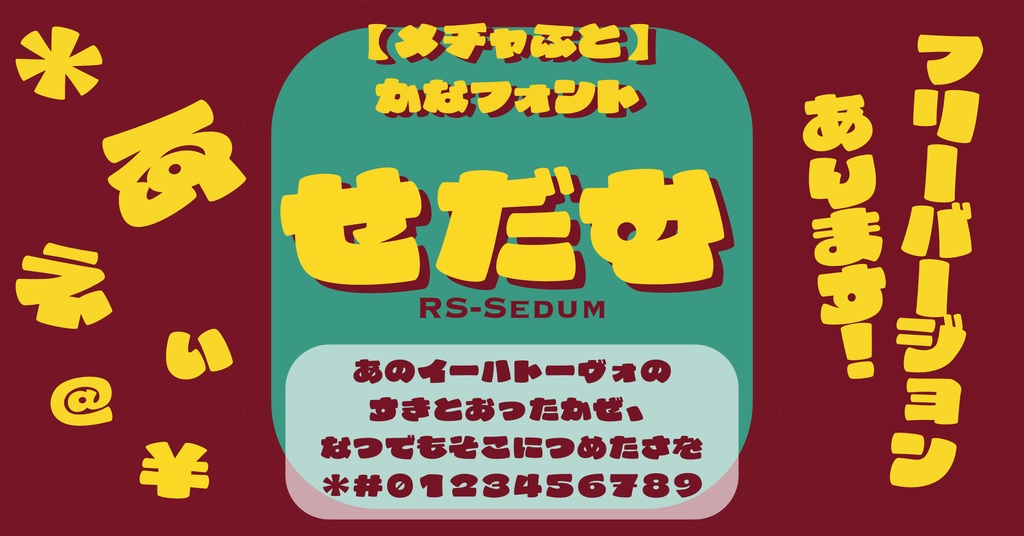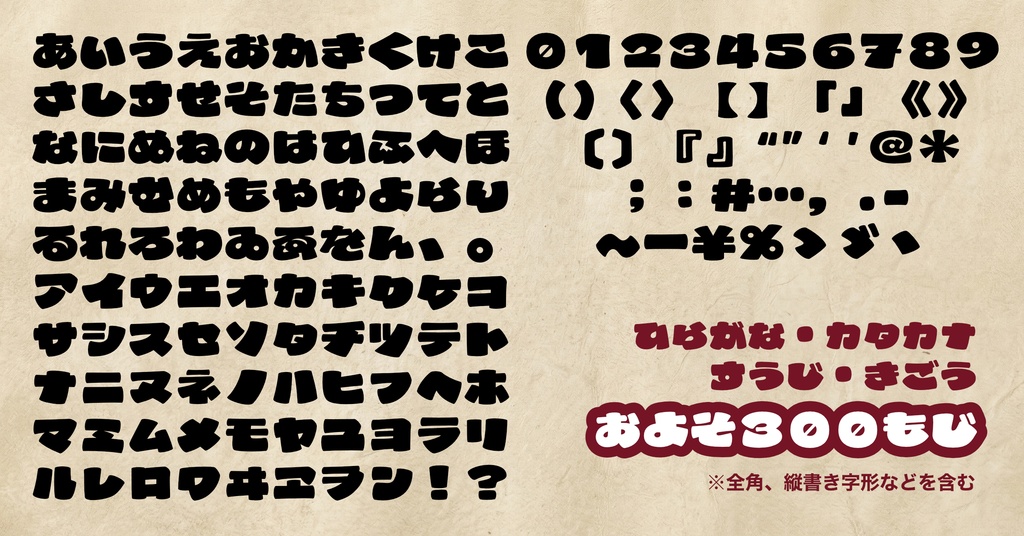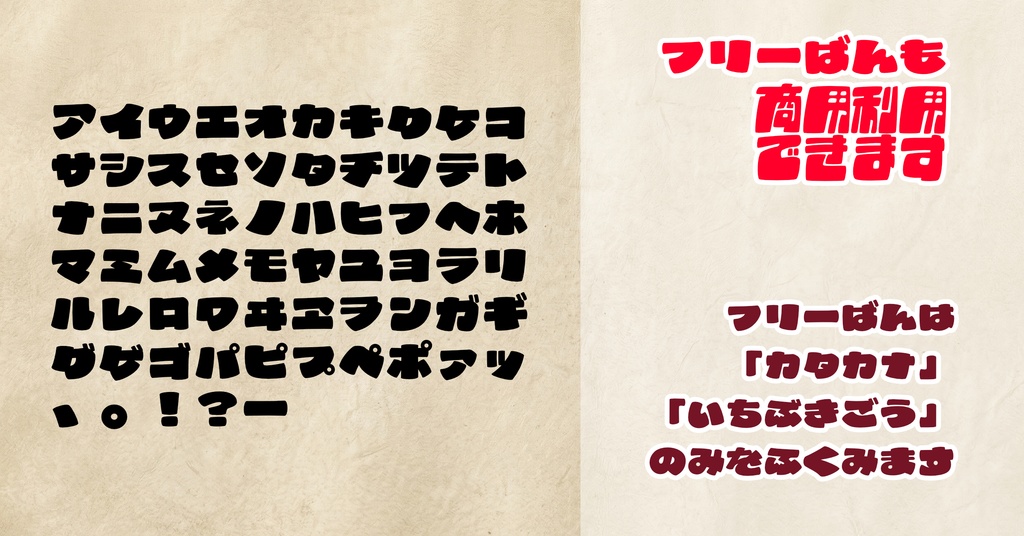
せだむ | フォント【フリー版】
クラシカルな強弱とモダンなラインを併せ持つ、ポップな極太ディスプレイ書体です。 インパクト抜群の極太ウエイトで、動画のサムネイル、同人誌のタイトルロゴ、ポスターの見出しなど、文字をしっかり目立たせたいデザインにぴったりです! 多肉植物のようにモチモチぷっくりしたフォルムであることから、その仲間である「セダム」を書体の名前に選びました!